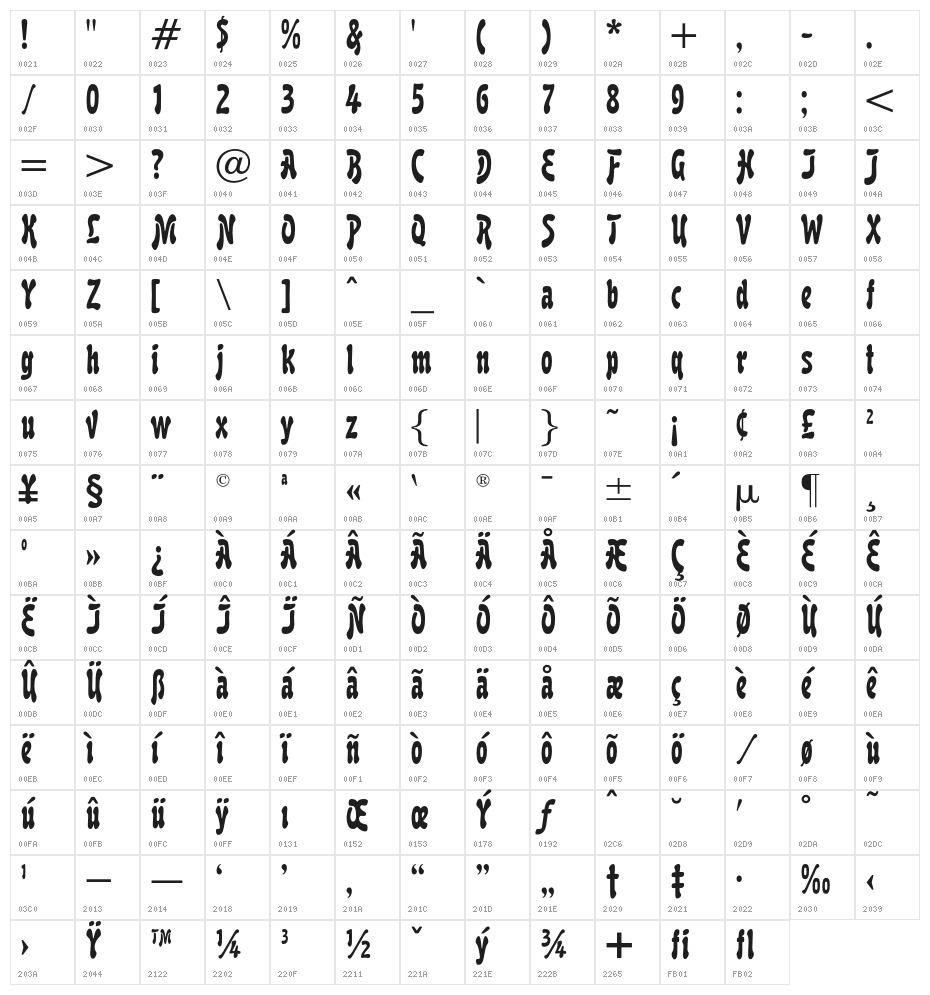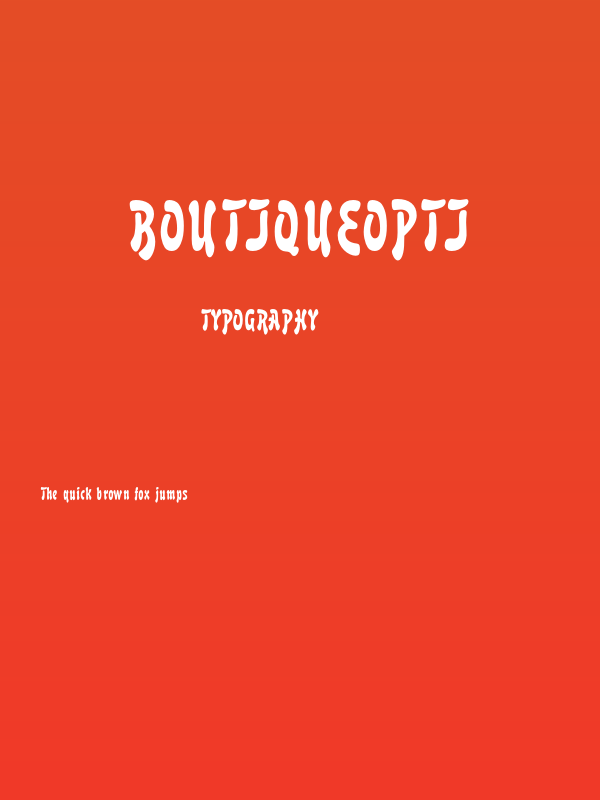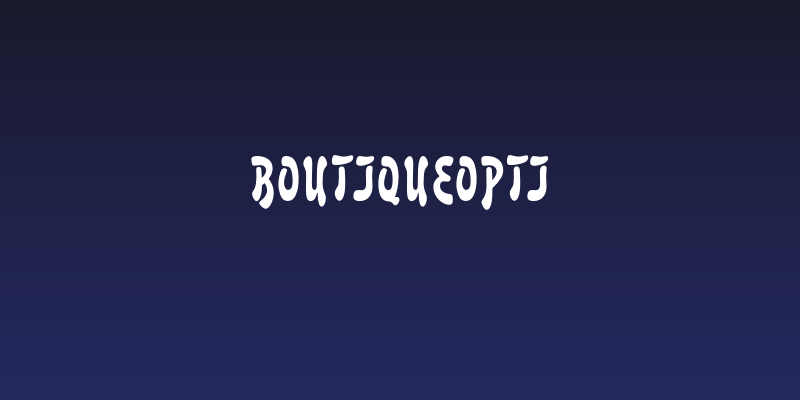
BoutiqueOpti Font
| Gesamtstil | Vintage |
| Vorgeschlagene Projekte | Ideal for vintage-themed posters, playful branding, children's books, and creative advertisements. |